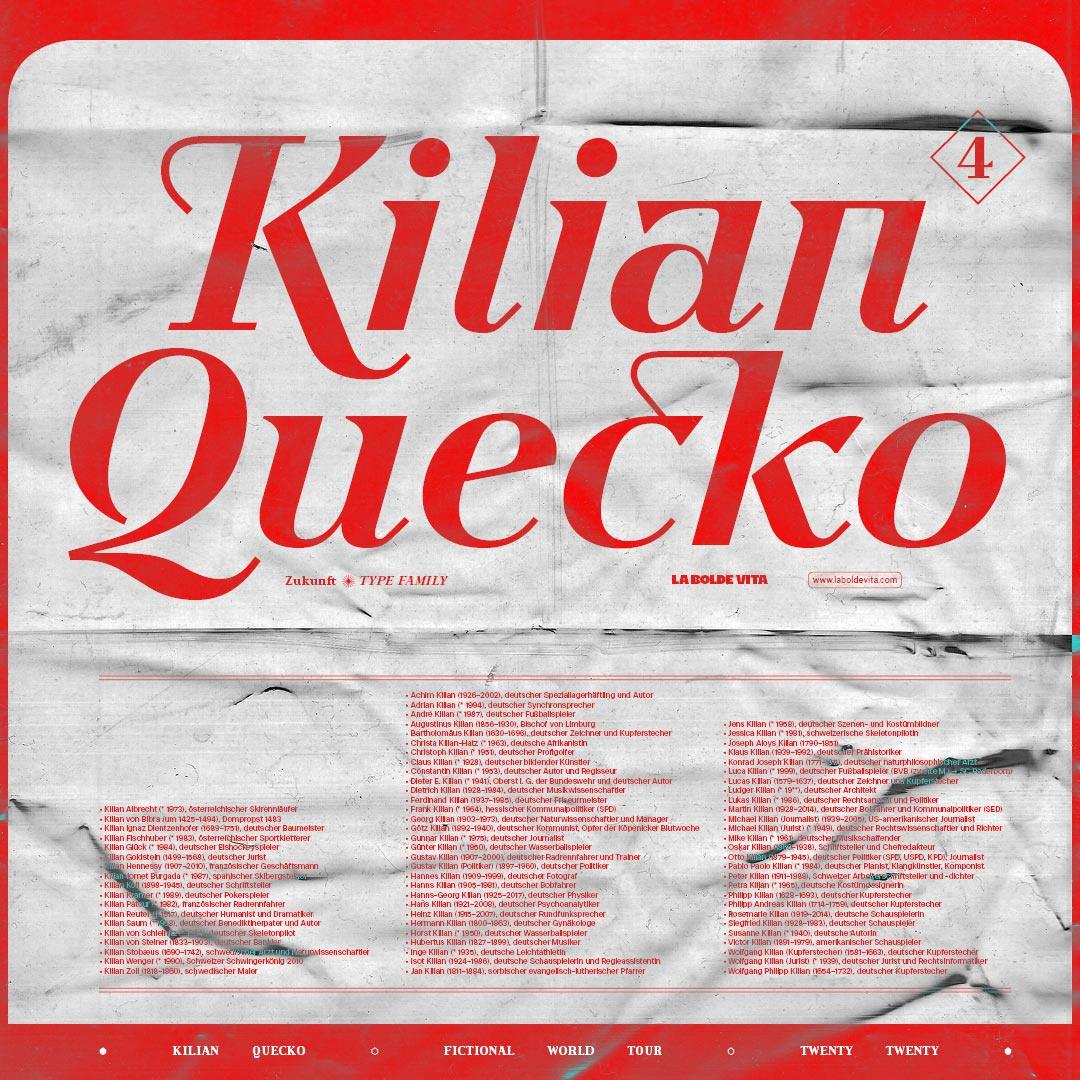
Zukunft Font
Description de Zukunft Font
La famille de polices Zukunft est la renaissance des polices Didone, conçues avec le souffle du look futuriste. Tout en conservant des proportions traditionnelles, le design adopte une approche moderne : les lettres sont comme tapées sur un ordinateur, les empattements sont triangulés, les joints sont carrés et les horizontales sont droites.
En plus du style Regular utilisé pour le corps du texte qui est le mieux adapté, la variante Italique restaure la fluidité et l’expressivité nécessaires lorsqu’il s’agit d’un usage décoratif ciblé. Découpe d’affichage, contraste élevé et empattements nets, cela convient parfaitement aux titres et aux affiches, comme celui-ci par exemple.
Comparé à nos autres modèles, Zukunft est plutôt conservateur mais il peut être utilisé dans presque tous les projets de conception. Que vous utilisiez des paragraphes courts, un titre ou une image de marque, les nombreux choix proposés ici conviendront et seront légèrement différents des autres. Bien sûr, vous feriez mieux d’explorer les nombreuses possibilités offertes par les nombreuses variantes des lettres et des chiffres, des symboles spéciaux et des majuscules italiques de Zukunft.